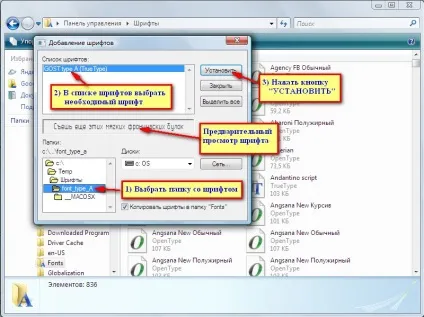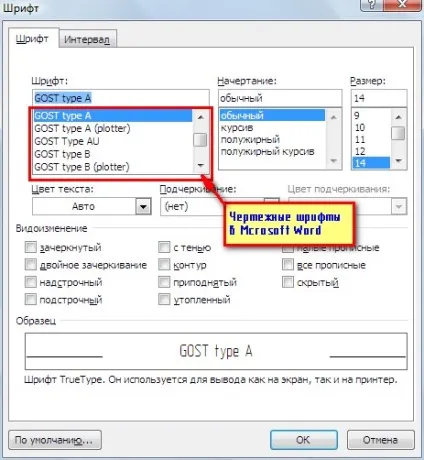
Отже, сьогодні я розповім вам ще про одне корисне прийомі (як модно зараз говорити - фішці) роботи зі шрифтом в програмі sPlan 7
Якщо вам доводиться креслити схеми по ГОСТ то, напевно, знаєте, що у всіх кресленнях для нанесення написів використовуються спеціальні креслярські шрифти.
Креслярські шрифти встановлює ГОСТ 2.304-81. До складу креслярських шрифтів входить український, латинський і грецький алфавіти, арабські і римські цифри, а також знаки.
ГОСТ 2.304-81 встановлює чотири типи шрифтів:
тип А без нахилу
тип А з нахилом близько 75 °;
тип Б без нахилу;
тип Б з нахилом близько 75 °
Розмір шрифту h визначається висотою прописних літер (в мм). ГОСТ 2.304 - 81 встановлює наступні розміри шрифтів: 2,5; 3,5; 5; 7; 10; 14; 20; 28; 40.